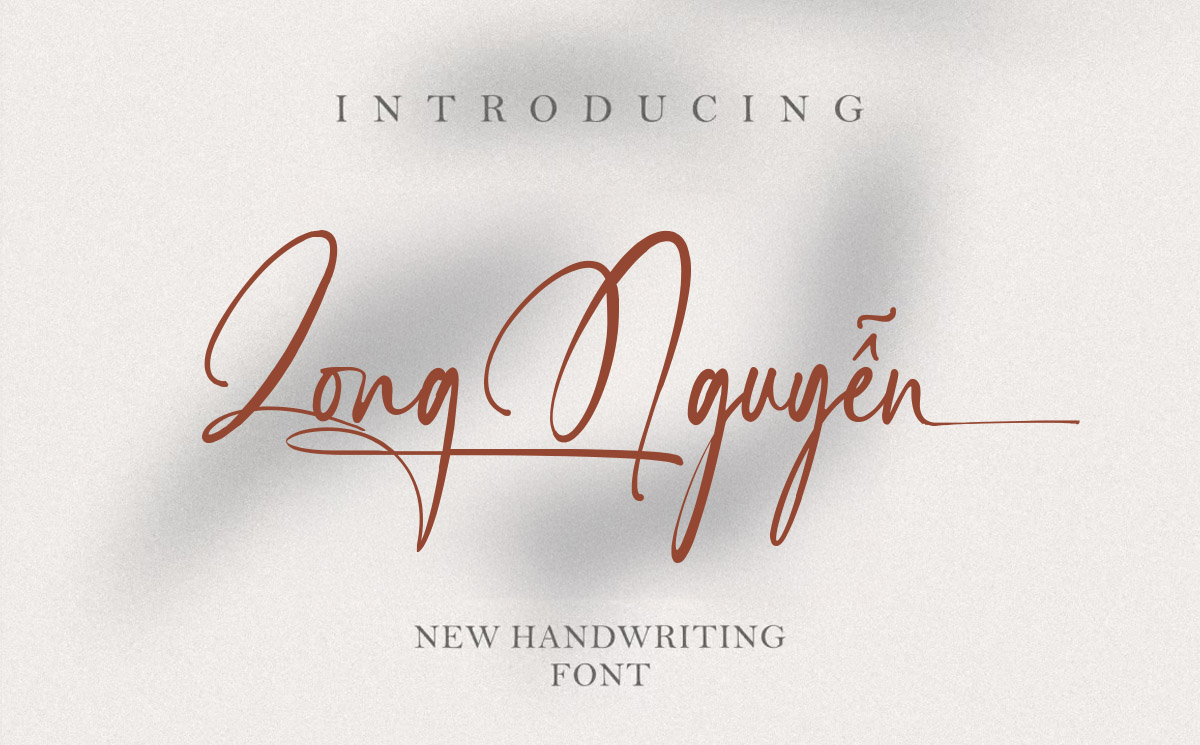
Trong nghệ thuật thiết kế ấn phẩm cưới và sự kiện cao cấp, typography giữ vai trò cốt lõi trong việc định hình phong cách và truyền tải cảm xúc trọn vẹn đến người nhận. TH Signatura Việt Hoá là bộ font chữ viết tay dạng chữ ký mềm mại, mang đến vẻ đẹp lãng mạn, tinh tế và vô cùng sang trọng cho các mẫu thiệp cưới hiện đại. Với sự tỉ mỉ trong từng đường nét uốn lượn cùng khả năng hiển thị tiếng Việt hoàn hảo, đây chính là sự lựa chọn ưu việt cho các designer và cặp đôi muốn tạo dựng dấu ấn cá nhân độc đáo trong ngày trọng đại.
Font Chữ Viết Tay, Chữ Ký Mềm Mại Cho Thiệp Cưới, Đám Cưới TH Signatura Việt Hoá – Điểm Nhấn Nghệ Thuật Cho Ấn Phẩm Ngày Cưới
Một tấm thiệp cưới hoàn hảo không chỉ cung cấp thông tin về lễ cưới mà còn thể hiện gu thẩm mỹ và tình yêu ngọt ngào của đôi lứa. Sự xuất hiện của các nét chữ ký mềm mại, tự nhiên sẽ lập tức nâng tầm giá trị thẩm mỹ cho toàn bộ thiết kế, biến những dòng chữ đơn thuần thành tác phẩm nghệ thuật thu nhỏ. Font chữ TH Signatura Việt Hoá được sáng tạo nhằm đáp ứng xu hướng thiết kế thiệp cưới tối giản nhưng tinh tế (Minimalist & Luxury Wedding Style) đang rất được ưa chuộng hiện nay. Không chỉ dừng lại ở các nét chữ cơ bản, font chữ còn thể hiện chiều sâu cảm xúc nhờ nhịp điệu nét thanh nét đậm tự nhiên như chữ ký thủ công của các nghệ nhân calligraphy.
1. Nét Chữ Ký Bay Bổng, Uốn Lượn Tự Nhiên Và Sang Trọng
TH Signatura Việt Hoá gây ấn tượng mạnh mẽ bởi hệ thống nét chữ uốn lượn tinh tế, miêu tả chân thực từng đường nét của một chữ ký nghệ thuật. Các đường nét được thiết kế với sự nhịp nhàng giữa nét thanh mảnh và nét đậm chắc chắn, tạo cảm giác mượt mà và chuyển động sống động trên mặt giấy. Dù bạn sử dụng font chữ này cho tên chú rể cô dâu, chữ “Mời dự lễ cưới” hay các câu chúc lãng mạn, nét chữ vẫn luôn giữ được sự thanh thoát, kiều diễm mà không gây cảm giác sến sẩm hay rối mắt.
2. Tối Ưu Bộ Dấu Tiếng Việt Chuẩn Xác, Không Lệch Nét
Vấn đề phổ biến khi sử dụng các font chữ script nước ngoài là bộ dấu tiếng Việt thường bị lỗi, làm hỏng bố cục hoặc làm mất đi vẻ đẹp vốn có của nét chữ. TH Signatura Việt Hoá đã khắc phục hoàn toàn điểm yếu này nhờ quá trình Việt hóa kỹ lưỡng. Các dấu thanh như sắc, huyền, hỏi, ngã, nặng cũng như các dấu nón, dấu móc của các chữ cái Â, Ă, Ê, Ô, Ơ, Ư, Đ đều được thiết kế lại thủ công. Khoảng cách và độ cao của từng dấu được căn chỉnh hợp lý, giúp văn bản tiếng Việt hiển thị liền mạch, chuẩn mực và đạt tính thẩm mỹ cao nhất.</p>
3. Tích Hợp Hệ Thống Swashes Và Ligatures Phong Phú
Điểm đặc sắc giúp TH Signatura Việt Hoá trở thành font chữ hàng đầu cho thiệp cưới là kho ký tự thay thế (Alternate Glyphs) và các đường gạch chân nghệ thuật (Swashes) đa dạng. Người dùng có thể dễ dàng thêm vào các đường đuôi uốn lượn ở đầu hoặc cuối từ, tạo nên những đường chữ ký cá nhân hóa vô cùng đẳng cấp. Bên cạnh đó, tính năng Ligatures (nét nối đôi) giúp xử lý mượt mà các cụm chữ cái đi liền nhau, loại bỏ vẻ cứng nhắc và tạo cảm giác như toàn bộ văn bản được viết tay hoàn toàn bằng bút mực thủ công.
4. Ứng Dụng Đa Năng Cho Nhiều Phong Cách Thiết Kế
Không chỉ giới hạn trong các mẫu thiệp cưới hay thiệp mời báo hỷ, TH Signatura Việt Hoá còn thể hiện tính đa năng vượt trội trong nhiều lĩnh vực sáng tạo khác nhau. Bạn có thể sử dụng bộ font này để thiết kế logo thương hiệu cao cấp (như studio ảnh cưới, thương hiệu áo cưới, mỹ phẩm, thời trang), làm watermark bảo vệ bản quyền hình ảnh, trang trí bìa album ảnh cưới, thiết kế menu tiệc tiệc, hay tạo các bài đăng thu hút trên các nền tảng mạng xã hội như Facebook, Instagram, Pinterest.
5. Tương Thích Xuất Sắc Trên Mọi Nền Tảng Và Phần Mềm
Bí Quyết Phối Font TH Signatura Việt Hoá Cho Ấn Phẩm Đám Cưới Đạt Chuẩn Luxury
Để phát huy tối đa vẻ đẹp của TH Signatura Việt Hoá trong các mẫu thiệp cưới, việc kết hợp font chữ một cách khoa học và giàu tính thẩm mỹ là vô cùng quan trọng. Dưới đây là những nguyên tắc vàng từ các chuyên gia thiết kế đồ họa:
- Phối hợp cùng Font Serif hoặc Sans-Serif thanh lịch: TH Signatura Việt Hoá đóng vai trò là font chữ nghệ thuật (Display/Script Font), do đó nó nên được sử dụng cho các tiêu đề chính, tên chú rể – cô dâu. Đối với các đoạn thông tin chi tiết như ngày giờ, địa điểm tổ chức tiệc cưới, hãy kết hợp với một font chữ không chân (Sans-Serif) hiện đại hoặc font có chân (Serif) cổ điển để đảm bảo tính dễ đọc cho khách mời.
- Chú trọng khoảng trắng và tỷ lệ bố cục: Với đặc tính nét chữ uốn lượn bay bổng, TH Signatura Việt Hoá cần có khoảng không gian thoáng đãng chung quanh để các đường swashes tỏa sáng. Tránh đặt chữ quá sát viền hoặc xếp quá nhiều dòng chữ ký đè lên nhau gây cảm giác chật chội.
- Lựa chọn kỹ thuật in ấn và màu sắc thượng thượng: Nét chữ ký thanh mảnh của TH Signatura vô cùng phù hợp với kỹ thuật in ép kim vàng (Gold Foil), ép kim bạc hoặc dập nổi trên chất liệu giấy mỹ thuật có độ nhám nhẹ. Nhờ đó, hiệu ứng ánh kim sẽ làm nổi bật từng đường uốn lượn, mang lại vẻ đẹp sang trọng tuyệt đối cho bộ thiệp cưới.